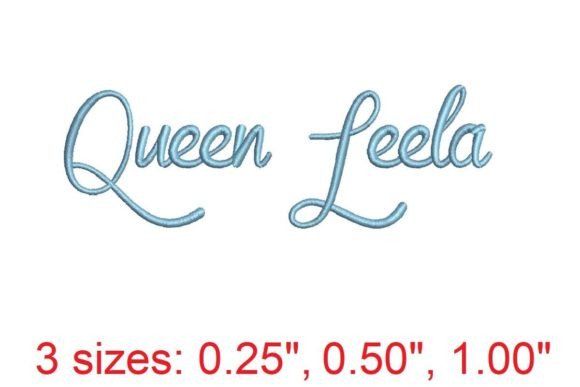
Queen Leela Embroidery Font
Việc tìm kiếm các thành phần thiết kế phù hợp có thể là một thách thức, nhưng Queen Leela Embroidery Font cung cấp một bộ sưu tập đặc biệt giúp nâng tầm công việc của bạn ngay lập tức.
Được chế tác với độ chính xác cao, Queen Leela Embroidery Font cung cấp các vector sạch, kiểu chữ mượt mà và giấy phép thương mại để bạn yên tâm.
Cho dù bạn đang tạo sản phẩm POD (In theo yêu cầu), thiệp mời đám cưới hay đồ họa mạng xã hội, Queen Leela Embroidery Font đều là một sự lựa chọn lý tưởng.